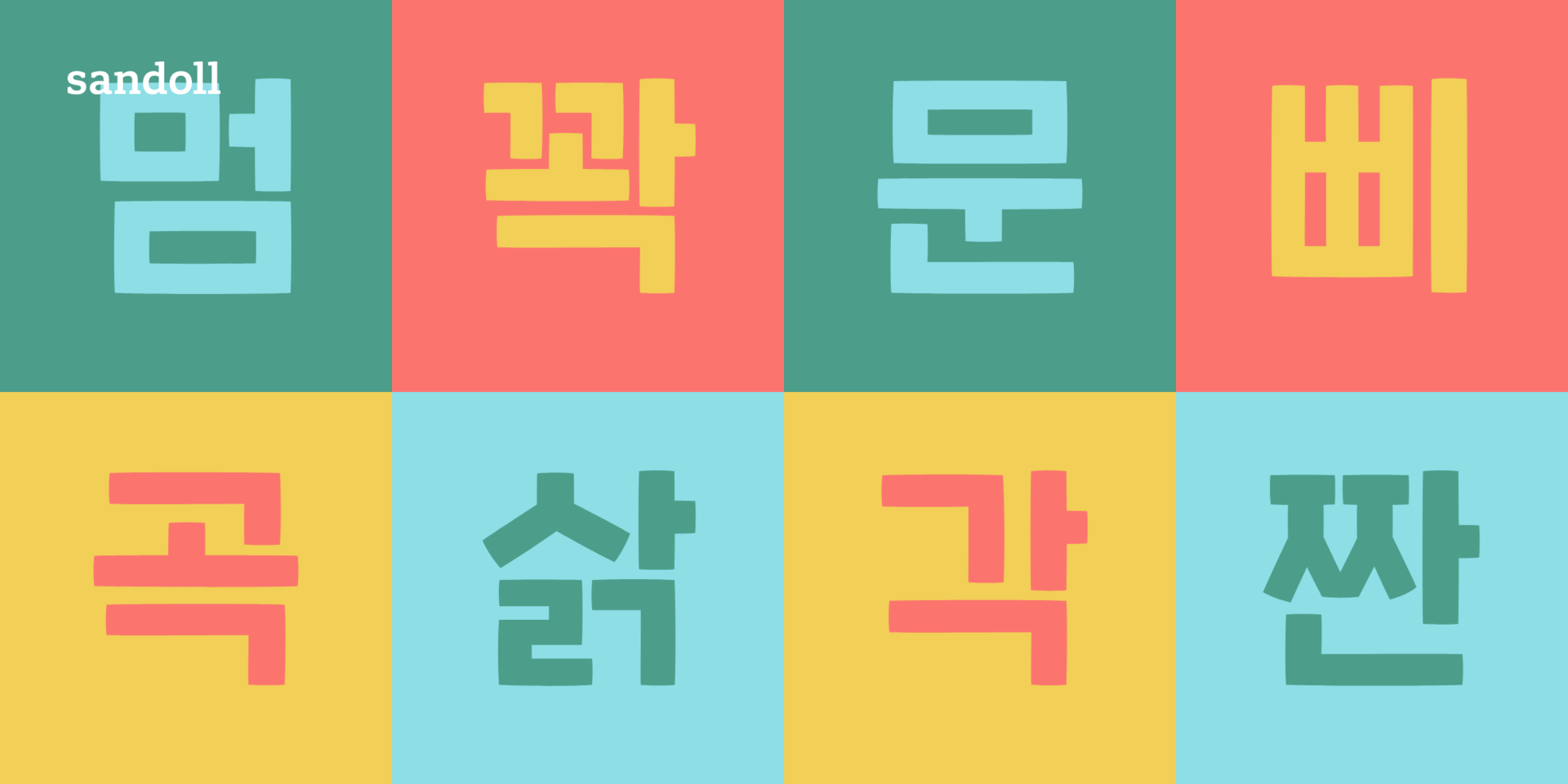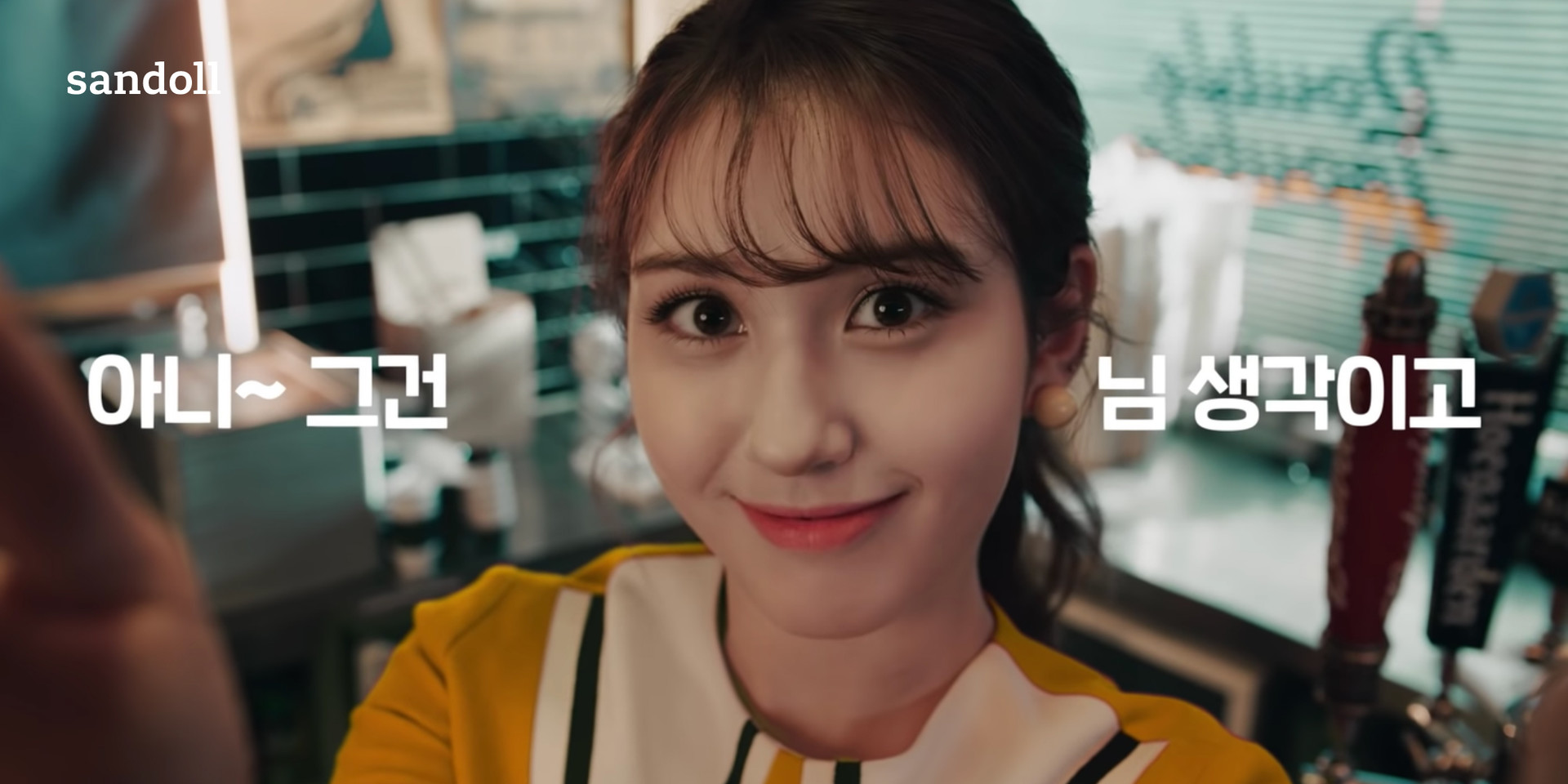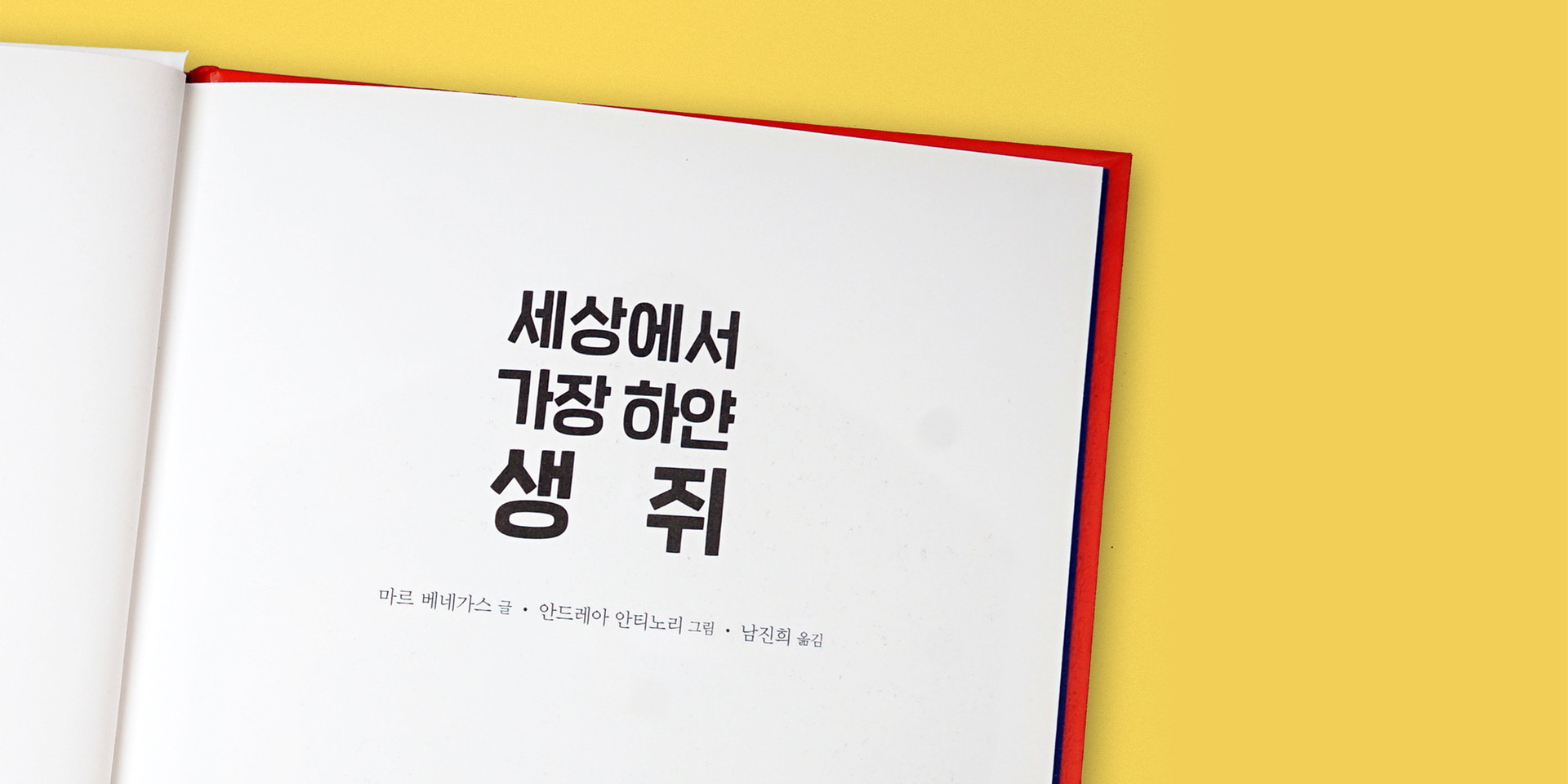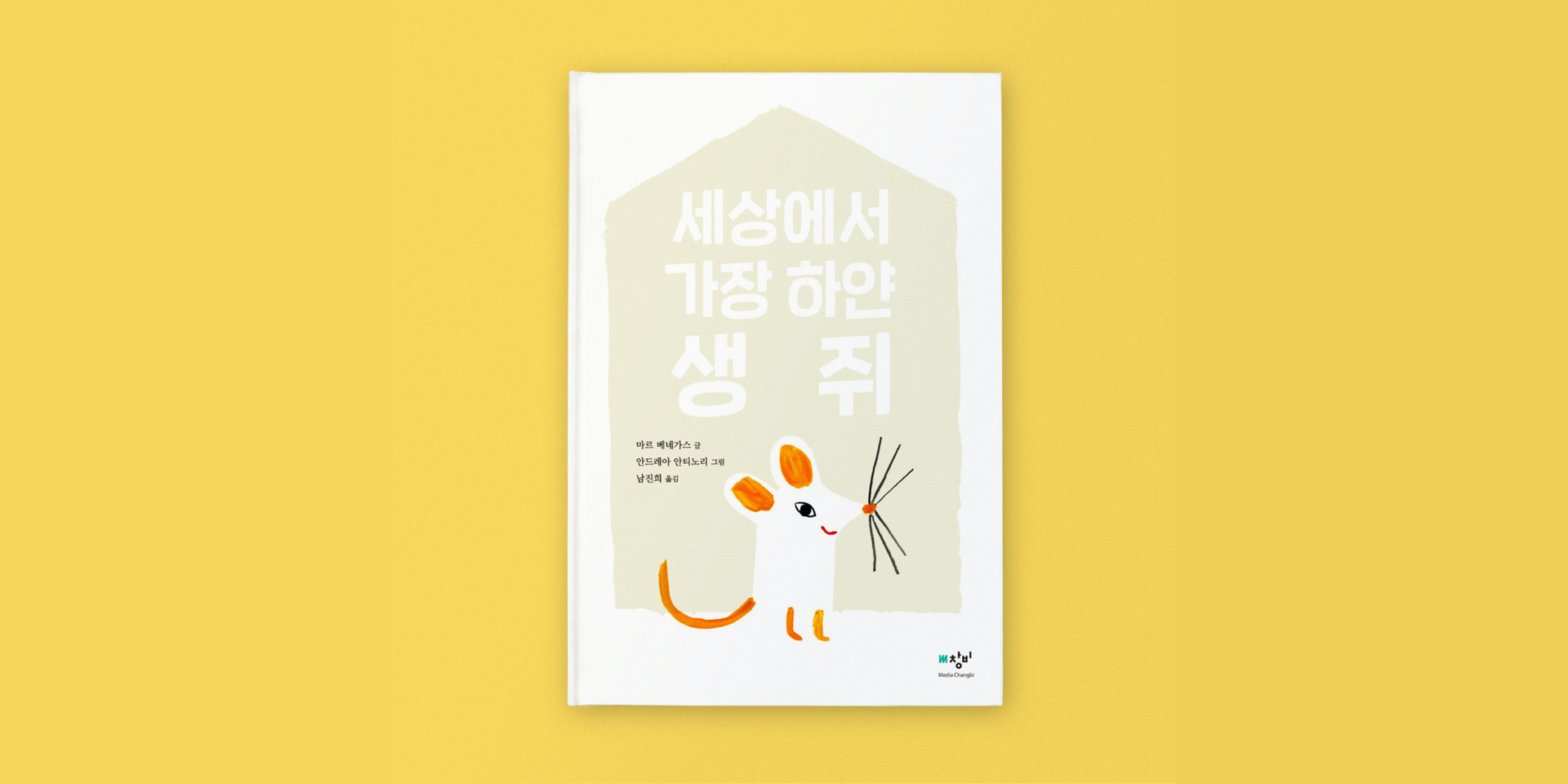
Sandoll 네모니
'네모니'는 기존의 꽉 찬 네모틀 서체보다도 훨씬 다양한 곳에서 사용이 가능하게끔 밝고 명랑한 인상을 특징으로 제작된 서체이다.직선적인 뼈대가 시원시원하고 쭉쭉 뻗은 느낌을 주고 있으며, 가로획과 세로획의 대비가 너무 강하지 않도록 미세한 양감을 부여하였다. Oblique를 함께 제작하여 젊고 감각적인 개성을 더욱 더 돋보이게 하였다.